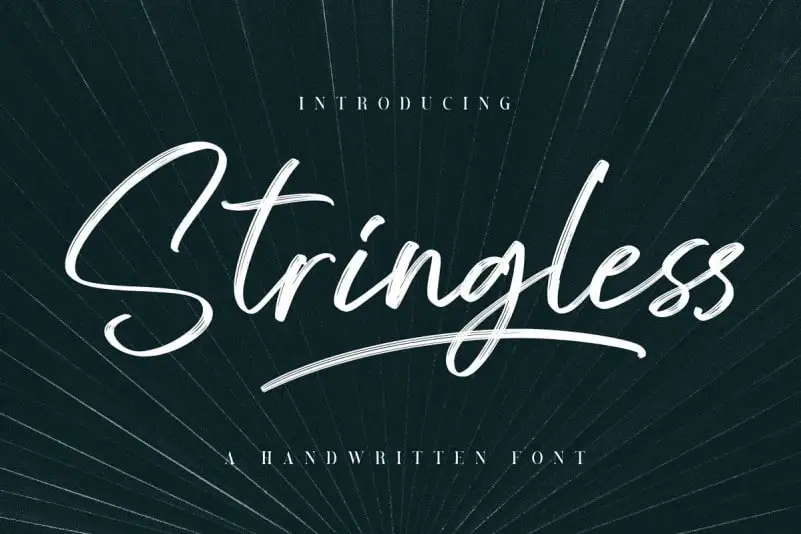
Stringless Brush Font – Download Grátis
A Stringless Brush Font é uma elegante tipografia script que transmite um sentimento natural e autêntico dos traços escritos a mão. Esta fonte criada à mão trará ao seu design um toque poético e natural para cada detalhe, perfeitamente combinado com o estilo hanzel do estúdio. Ideal tanto para aplicar em branding, anúncios e headlines como também em designs de embalagens, ela destaca-se por ser uma fonte que reflete a essência da arte manual, com traços ressaltados e escrita rapidamente, relaxada, através de um pincel seco. A versão dupla do tipo oferece o elemento único quando combinada, e também complementa perfeitamente com swashes. Uma fonte que certamente valorizará sua próxima criação gráfica.